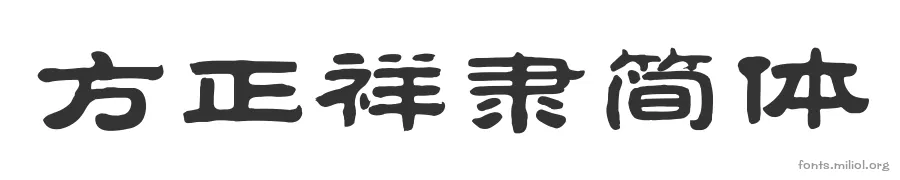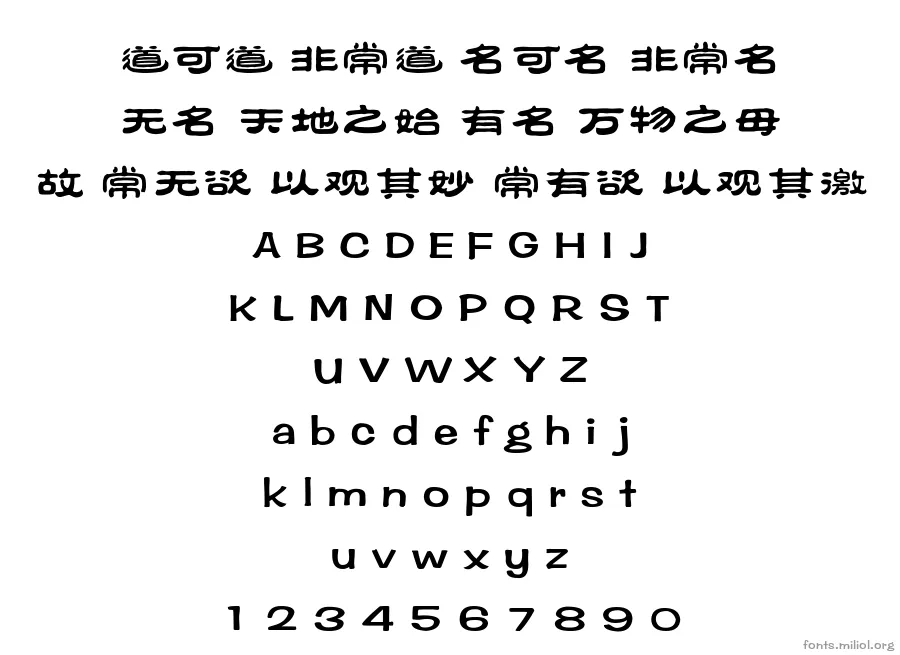
## 方正祥隶简体:传统与现代交融的书法艺术
方正祥隶简体是一款融合传统隶书韵味与现代设计美学的电脑字体,其编号FZXiangLi-S17S和FZXIANGLJW--GB1-0体现了方正字库严谨的字体编码体系。这款字体在笔画处理上保留了隶书特有的"蚕头燕尾"特征,横画起笔圆润如蚕头,收笔上扬似燕尾,同时通过简化的笔形设计,使其更符合现代屏幕显示需求。
设计师在创作过程中,既遵循了《乙瑛碑》《礼器碑》等汉代经典隶书的结字规律,又针对数字时代的使用场景进行了优化调整。字体重心平稳,结构疏密得当,撇捺舒展而不失力度,特别适合用于文化类书籍、传统品牌标识等需要展现文化底蕴的场合。其GB1-0编码表明该字体完全支持国家标准GB2312-80字符集,包含6763个常用汉字,能够满足日常中文排版的基本需求。
这款字体的独特之处在于,它既能让现代读者感受到隶书古朴典雅的艺术魅力,又能保证在各类数字媒介上的清晰可读性,实现了书法艺术与实用功能的完美平衡。